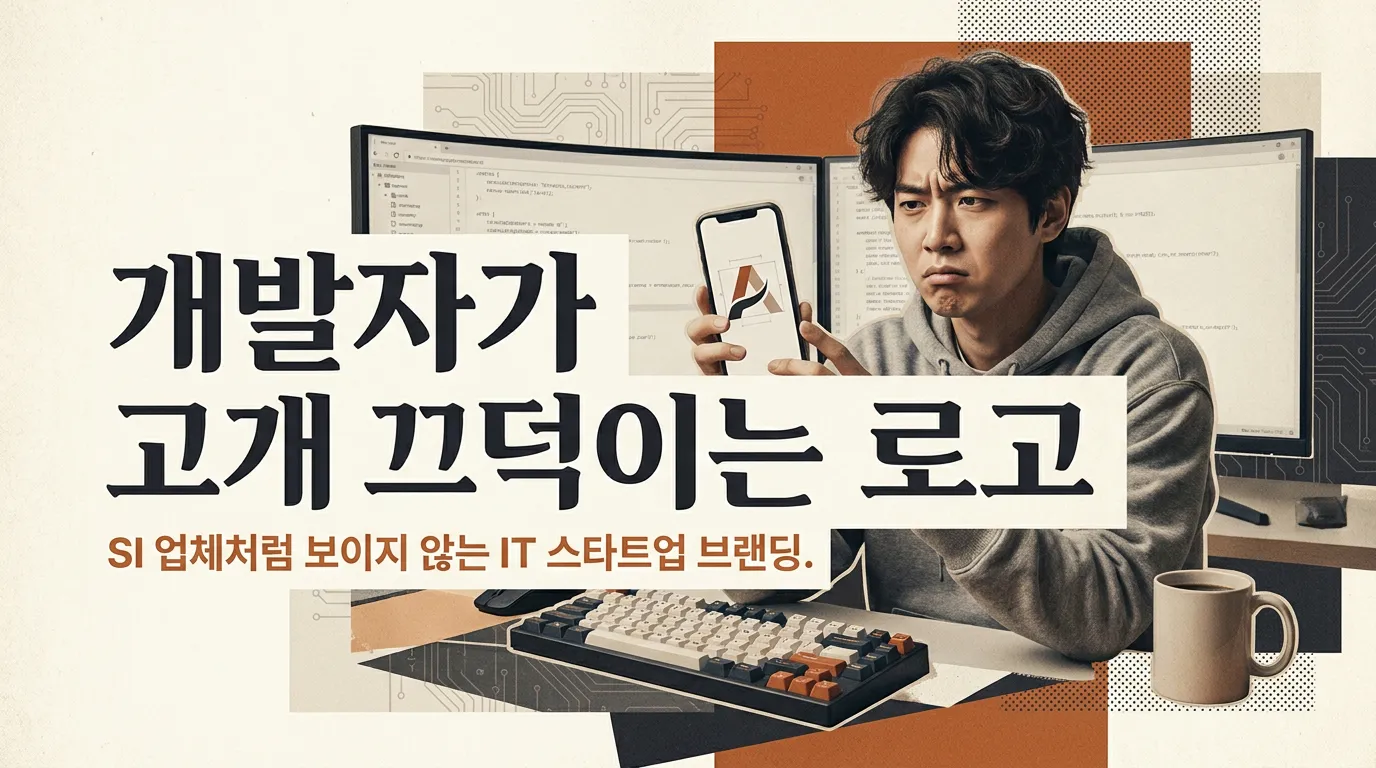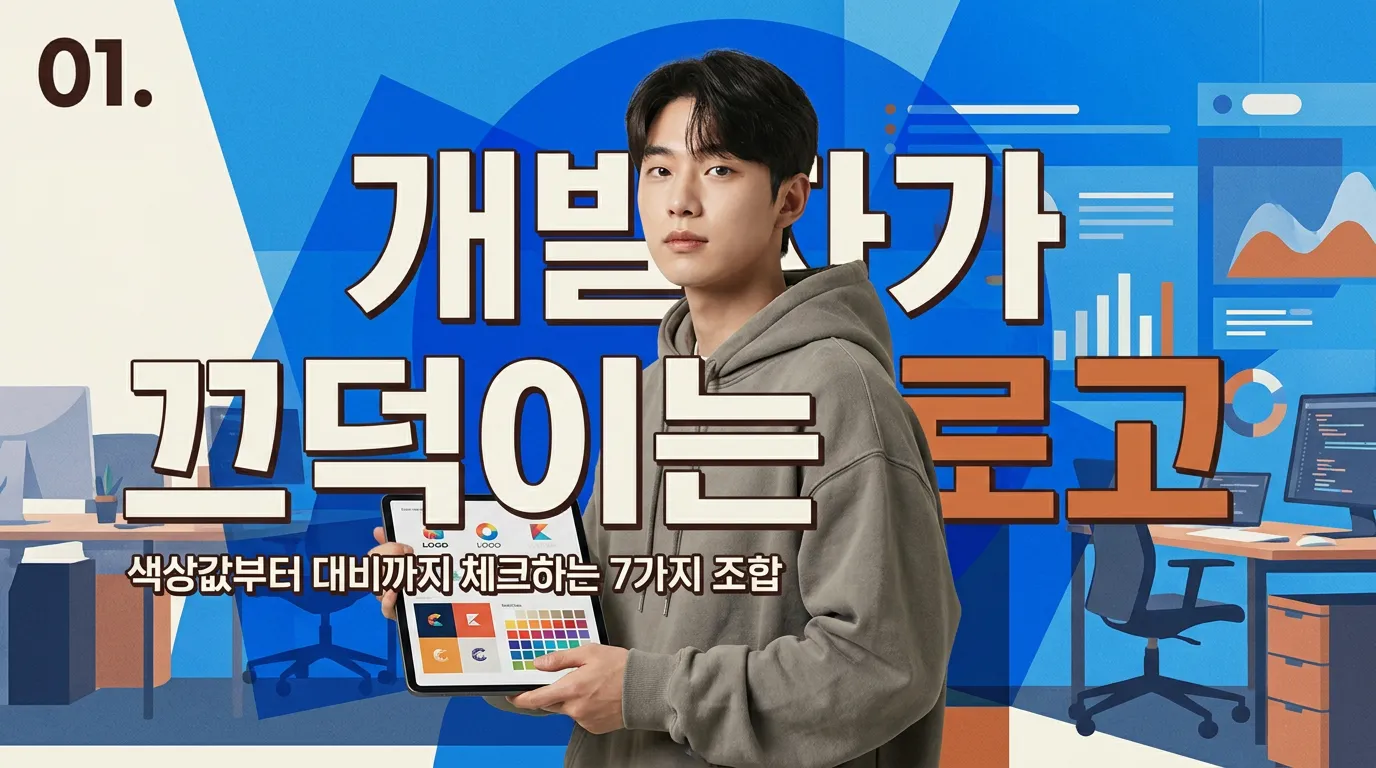
IT 스타트업 로고 디자인, 개발자가 먼저 고개 끄덕이는 색·폰트 7조합
기술력 있어 보이는 IT 스타트업 로고 디자인 색상·폰트 조합 7가지. SaaS, AI, 보안, 데이터 브랜드에 바로 적용할 기준.
IT 스타트업 로고 디자인, 개발자가 먼저 고개 끄덕이는 색·폰트 7조합
예쁜데 왠지 SI 업체 같아 보이는 로고, 개발자 채용 페이지에 올리는 순간 티가 납니다.
기술력은 왜 파란색 하나로 안 보일까요?
IT 스타트업 로고 디자인에서 가장 많이 나오는 요청이 “기술력 있어 보이게”입니다. 그런데 대표님, 여기서 파란색만 고르면 거의 같은 얼굴이 됩니다. 클라우드도 파랑, 핀테크도 파랑, 협업툴도 파랑이니까요.
저라면 색을 먼저 고르지 않습니다. 먼저 정합니다. “우리는 안정적인 인프라인가, 빠른 자동화인가, 보안인가, 데이터 분석인가.” 그다음 색을 붙입니다. Google Material Design도 브랜드를 대표하는 primary color와 보조 색, 밝고 어두운 변형을 나눠 UI에 쓰라고 말합니다. 로고 색도 똑같습니다. 한 색이 아니라 ‘역할이 나뉜 색’이어야 개발 화면까지 버팁니다.
개발자가 싫어하는 로고는 어디서 갈릴까요?
개발자는 장식보다 규칙을 봅니다. 색상값이 애매하거나, 다크모드에서 죽거나, 폰트가 웹에서 깨지면 바로 “이거 운영하기 힘들겠는데요”가 나옵니다.
그래서 로고 단계부터 HEX 컬러, 대비, 폰트 대체값까지 잡아야 합니다. W3C의 WCAG 기준은 일반 텍스트 대비를 4.5:1 이상으로 봅니다. 로고가 UI 버튼, 관리자 페이지, 피치덱, 깃허브 README에 같이 쓰일 브랜드라면 이 숫자는 꽤 현실적인 기준입니다.
다크모드 대시보드 위에 적용된 로고와 컬러 토큰
바로 써도 어색하지 않은 7가지 조합은?
1. 딥네이비 #0B1220 + 시안 #22D3EE / Pretendard + IBM Plex Mono
B2B SaaS, API, 클라우드에 잘 맞습니다. 네이비가 바닥을 잡고, 시안은 기술 신호처럼 씁니다. Mono는 한 단어 전체가 아니라 심볼 안 숫자나 짧은 태그에만 쓰세요.
2. 차콜 #111827 + 그린 #10B981 / Inter + JetBrains Mono
개발툴, DevOps, 자동화 서비스에 좋습니다. 그린은 “성공 상태”와 맞닿아 있어 제품 화면으로 확장하기 쉽습니다.
3. 코발트 #2563EB + 쿨그레이 #F3F4F6 / Noto Sans KR + Roboto
대중형 앱, 협업툴, 플랫폼 스타트업에 안전합니다. 한글 서비스라면 국문 가독성이 먼저입니다. 로고 영문만 멋지고 한글 서비스명이 따로 놀면 출시 후 계속 불편합니다.
4. 블랙 #050505 + 바이올렛 #7C3AED / Space Grotesk + Pretendard
AI, 데이터, 크리에이터 툴에 어울립니다. 단, 그라데이션을 로고 본체에 넣기보다 배경 그래픽으로 빼는 편이 오래 갑니다.
5. 슬레이트 #0F172A + 오렌지 #F97316 / SUIT + IBM Plex Sans
보안, 모니터링, 인프라 경고 시스템에 맞습니다. 오렌지는 많이 쓰면 불안해 보입니다. 점, 라인, 액센트로만 쓰세요.
6. 틸 #0F766E + 화이트 #FFFFFF / IBM Plex Sans + Noto Sans KR
헬스테크, ESG 데이터, B2B 분석 서비스에 좋습니다. IBM 디자인 언어도 블루 계열과 흑백, 그레이를 중심에 두고 다른 색을 목적 있게 쓰라고 봅니다. 결국 색은 분위기가 아니라 사용 규칙입니다.
7. 블루 #1D4ED8 + 퍼플 #9333EA / Sora + Pretendard
AI SaaS나 글로벌 툴에 잘 맞습니다. 단, 워드마크는 단색에서도 먼저 완성되어야 합니다. 색이 빠졌을 때 약한 로고는 투자자료에서 힘이 빠집니다.
폰트는 멋보다 운영 난이도로 고르세요?
로고 폰트는 앱 화면 폰트와 100% 같을 필요는 없습니다. 하지만 너무 멀어지면 브랜드가 둘로 쪼개집니다. 제가 현장에서 보면 초기 스타트업은 “로고용 폰트 1개 + 서비스용 국문 폰트 1개 + 코드 느낌 보조 폰트 1개”면 충분합니다.
IBM Developer가 IBM Plex Mono를 쓰는 이유도 개발 환경에 익숙한 인상을 만들기 위해서입니다. 이걸 그대로 베끼라는 뜻이 아닙니다. 개발자에게 통하는 느낌은 장식이 아니라 “코드, 토큰, 시스템으로 이어지는 질서”에서 나온다는 뜻입니다.
마크에서 IT 브랜드를 잡을 때도 로고 한 장보다 먼저 보는 게 이 부분입니다. 심볼이 앱 아이콘, 파비콘, 슬랙 프로필, 다크모드 헤더에서 같은 인상으로 살아남는지요.